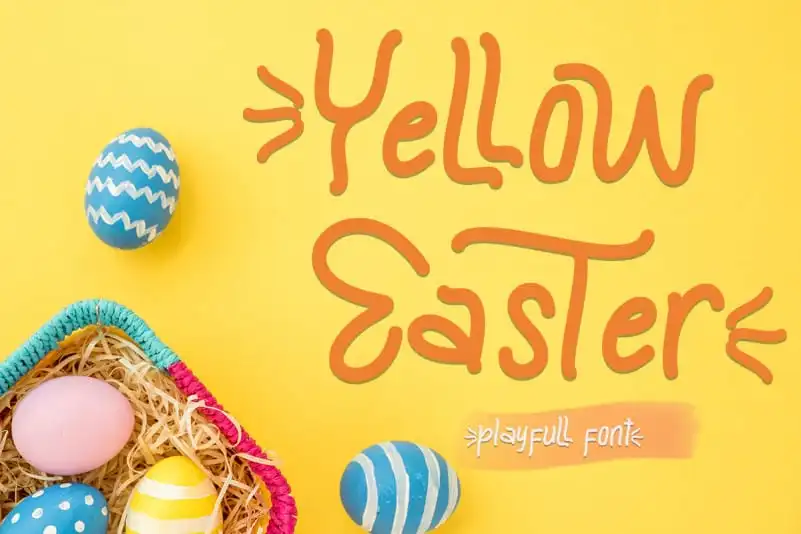
Yellow Easter Display Font – Download Grátis
A Yellow Easter Display Font é uma bela fonte ideal para aqueles que procuram algo único e encantador para celebrar o dia das Páscoas. Essa fonte foi projetada especialmente com um toque de simplicidade, tornando-a a escolha perfeita tanto para decorar cards festivos quanto para incorporar em logotipos ou materiais promocionais. Seu charme e versatilidade garantem que ela seja uma opção indispensável para qualquer projeto onde você deseja transmitir elegância através de letras. Esta fonte oferece um toque delicado às letras, decoradas com detalhes atraentes, tornando-a perfeita não apenas para celebrar o dia da Páscoa, mas também para promover seus produtos ou dar um toque criativo aos materiais de marketing e publicidade. É uma fonte de tamanho grande que funciona perfeitamente em cartazes, outdoors, estampas de camisetas e até mesmo em impressões digitais finas. Ela é perfeita tanto para personalizar sua decoração natalina quanto para criar um visual único para seu produto ou marca. A Yellow Easter Display Font é uma escolha inteligente para designers gráficos que buscam adicionar um toque especial a seus projetos visuais, tornando-os ainda mais memoráveis e atrativos.